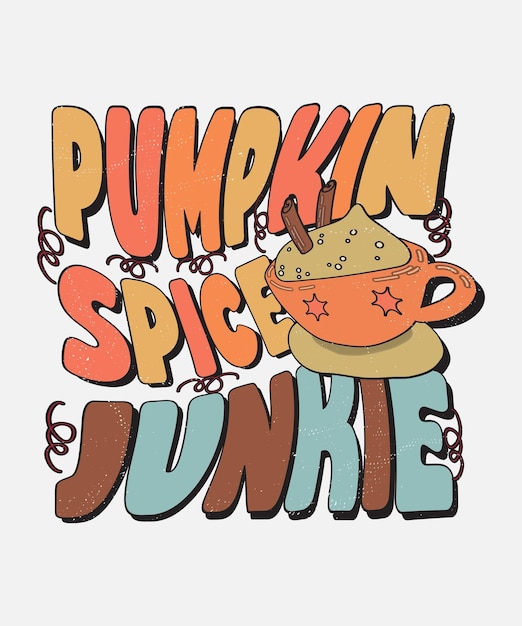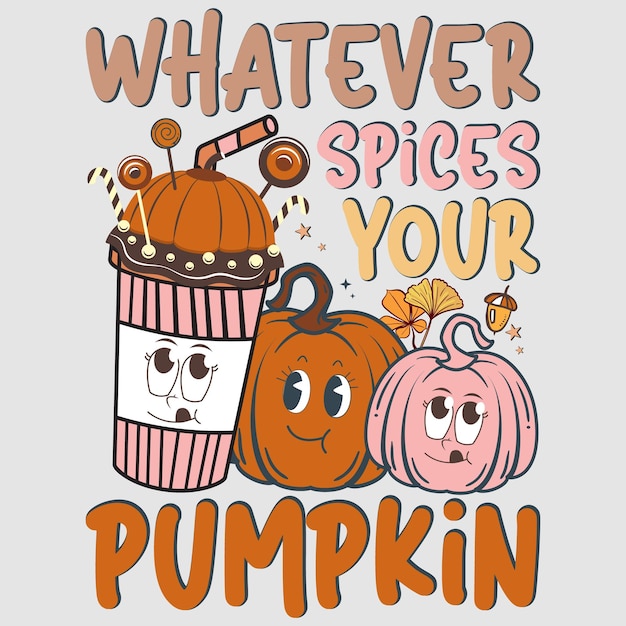
conception de lettrage de typographie automne groovy, conception de t-shirt de lettrage de Thanksgiving, t-shirt groovy
Conception de lettrage de typographie automne groovy, conception de t-shirt de lettrage de Thanksgiving, t-shirt groovy